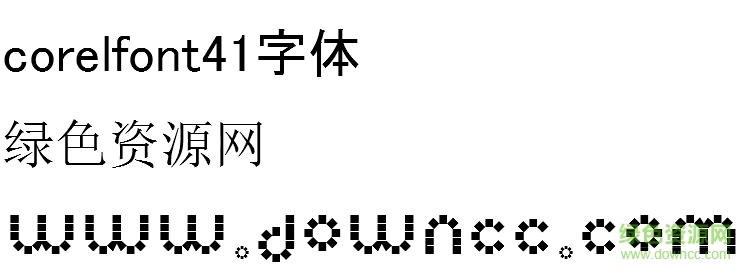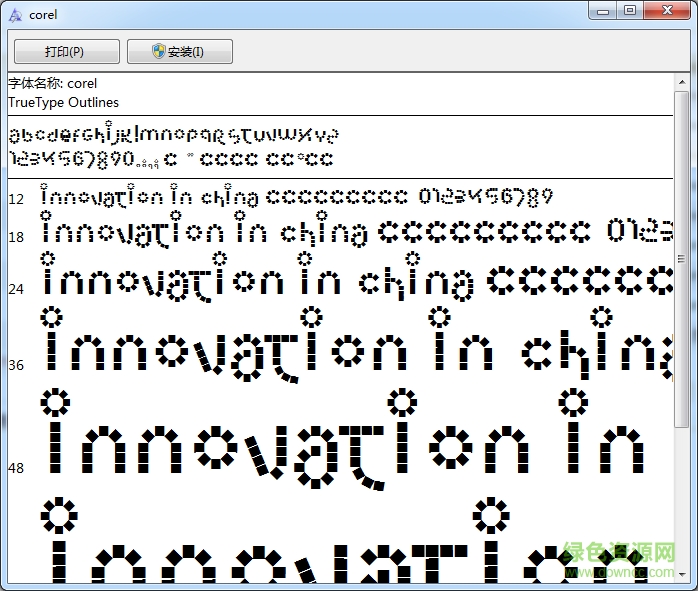
corelfont字體是一款英文藝術(shù)字體,該字體只對(duì)英文輸入有效,輸入中文不顯示,每一字符都由小方塊構(gòu)成,看起來有一種動(dòng)態(tài)美,感興趣的朋友就來綠色資源網(wǎng)體驗(yàn)吧!
corelfont是一款非常少見的英文字體,獨(dú)有的造型讓你的英文設(shè)計(jì)更有特色,可廣泛使用于平面設(shè)計(jì)、藝術(shù)設(shè)計(jì)、海報(bào)設(shè)計(jì)等行業(yè)!
corelfont,Corel字體,一種英文字體,根據(jù)Corel的標(biāo)志圖形設(shè)計(jì)的英文字體!